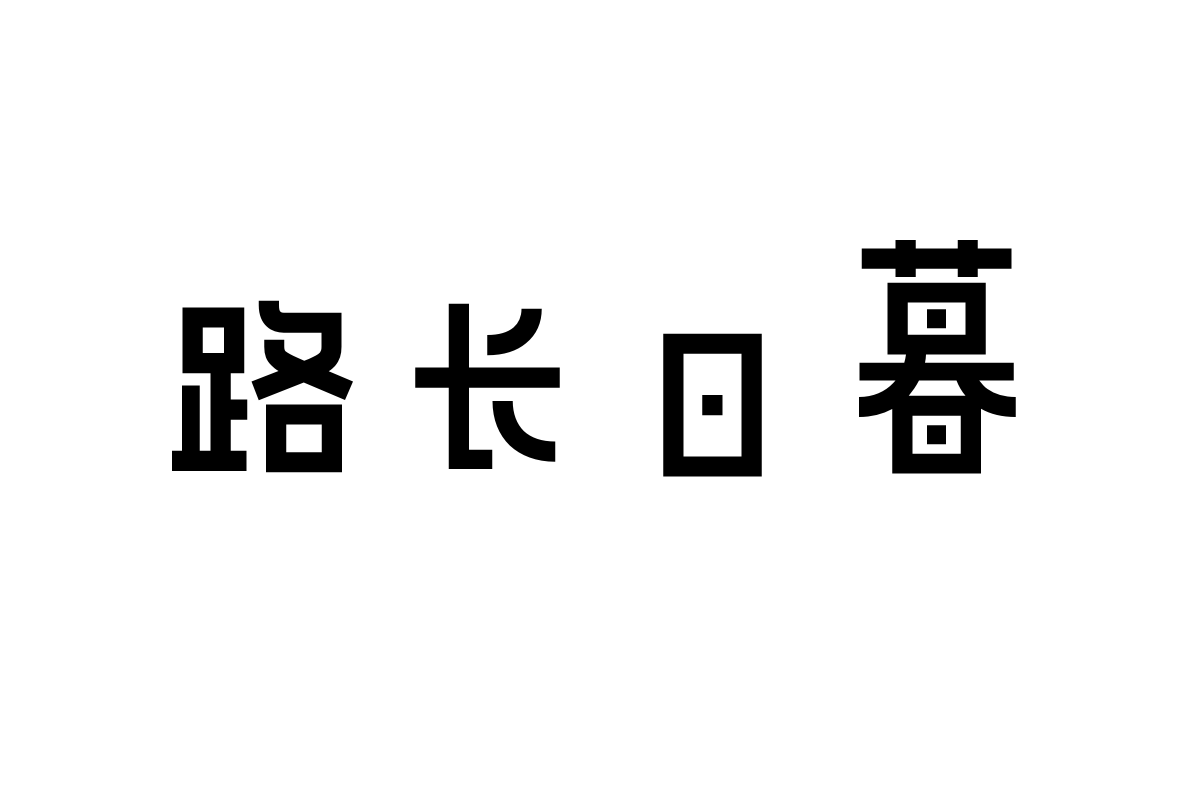
造字工房巧拼体是一款独特的字体,它由多个不同的字符组合而成。每个字符都经过精心设计和调整,以确保它们能够和谐地结合在一起,创造出独特的视觉效果。这种字体的特点是它的多样性和灵活性,使得它非常适合用于各种设计项目,如标志、海报、网页等。
造字工房巧拼体的特点包括:
1. 独特性:每个字符都是独立设计的,因此它具有很高的独特性。这使得它能够为设计项目提供独特的视觉元素。
2. 灵活性:由于每个字符都是独立的,所以你可以自由地组合它们,以创造出你想要的设计效果。这使得它非常灵活,可以适应各种不同的设计需求。
3. 易于使用:造字工房巧拼体的设计非常简单,你不需要特殊的技能就可以使用它。这使得它非常适合初学者和设计师。
4. 可定制性:虽然每个字符都是独立的,但你可以根据你的需要来定制它们。例如,你可以改变字符的大小、颜色或形状,以适应你的设计需求。
总的来说,造字工房巧拼体是一款功能强大且易于使用的字体,它能够满足各种设计项目的需求,并提供独特的视觉效果。